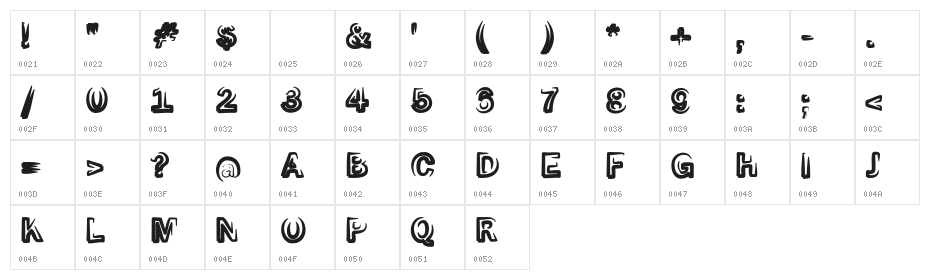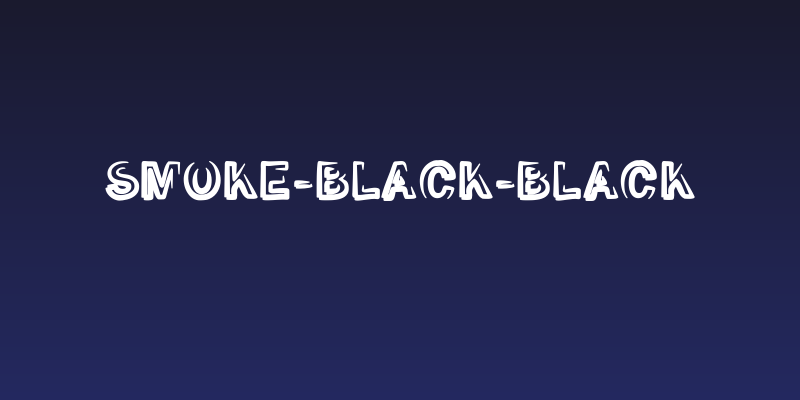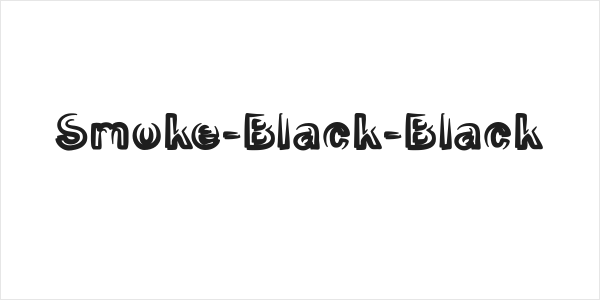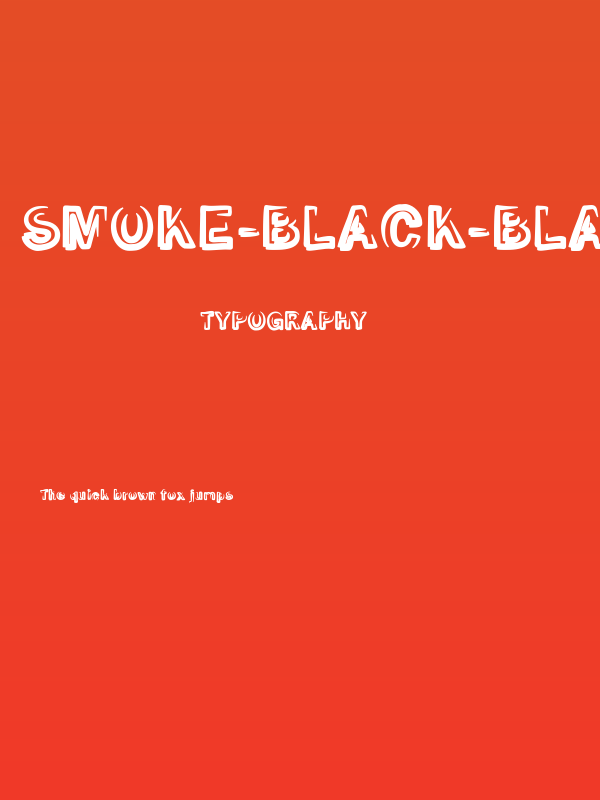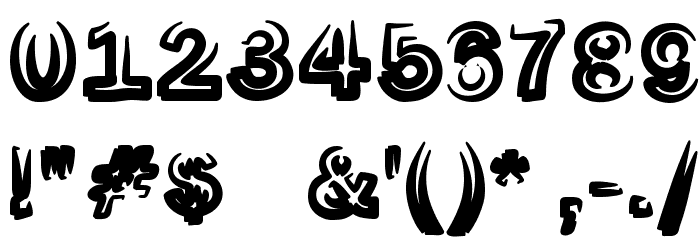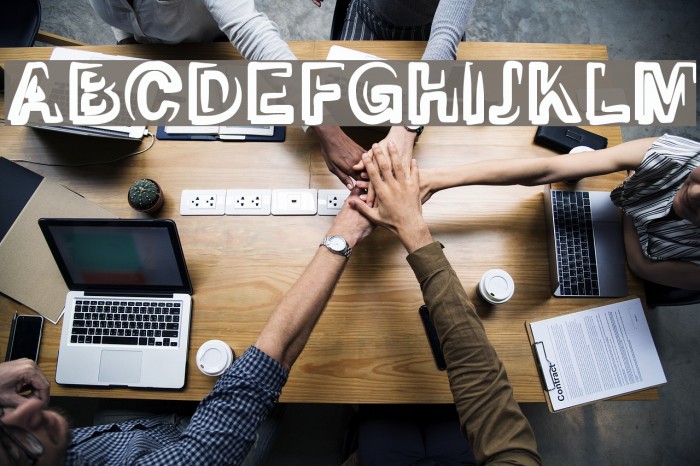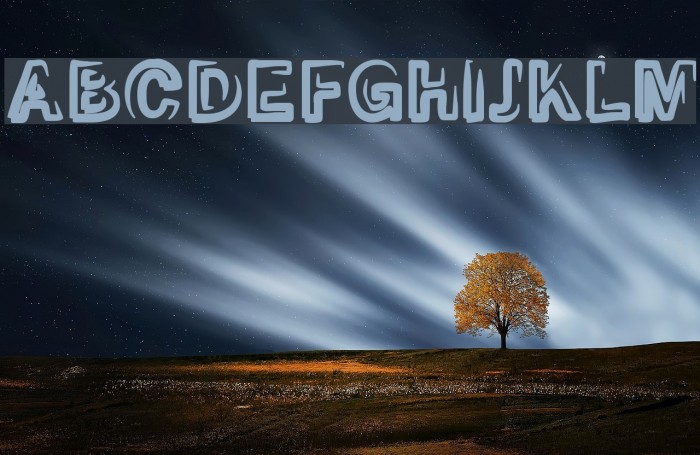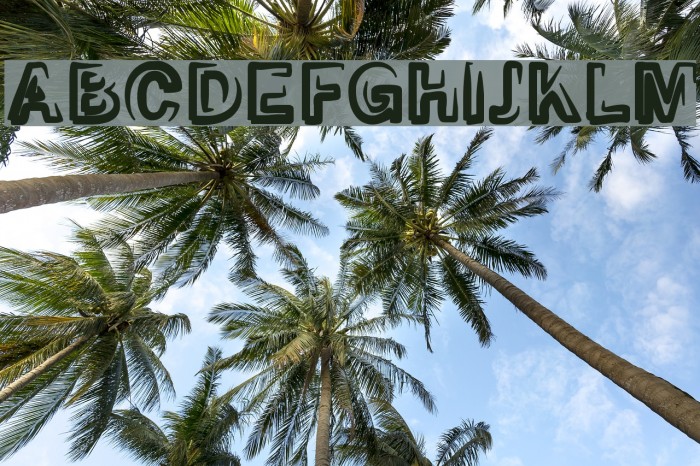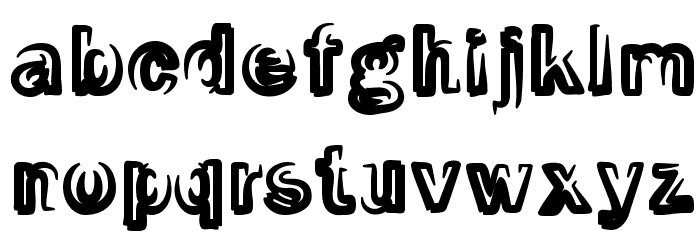
Smoke-Black-Black Font
| Progetti proposti | This font is perfect for posters, headlines, logos, and any design project that requires a bold and artistic touch. |